王僧虔简介
琅琊临沂人。南朝齐书法家。字简穆,王羲之四世族孙。官至尚书令。喜文史,善音律,工真、行书。书承祖法, 丰厚淳朴而有骨力。《齐书》本传称:“僧虔善隶楷书, 宋文帝见其书素扇,叹曰:‘非惟迹逾子敬,方当器雅过之。’”唐代张怀瓘《书断》称:“祖述小王,尤尚古直,若溪涧含冰, 冈峦被雪, 虽极清肃,而寡于风味。”窦臮《述书赋》称其书:“致丰富,得能失刚。鼓怒骏爽,阻负任强。然而神高气全,耿介锋芒。发卷伸纸,满目辉光。”墨迹有《王琰帖》。著有《论书》、《笔意赞》等。
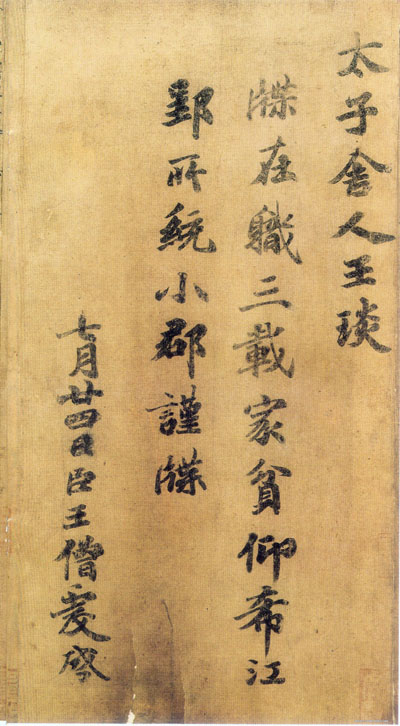
《王琰帖》(又称《太子舍人帖》、《在职》),见于辽宁省博物馆藏的《唐摹万岁通天帖》,传为王僧虔书,唐摹本。
释文:
太子舍人王琰
牒。在职三载,家贫,仰希江
郢所统小郡,谨牒。
七月廿四日臣王僧虔启。